Bạn cảm thấy kiểu chữ mặc định trên điện thoại quá nhàm chán và bạn muốn thay đổi kiểu chữ trên điện thoại mình bắt mắt hơn? Bạn gặp khó khăn trong việc chỉnh cỡ chữ trên điện thoại? Đừng lo lắng, bài viết này sẽ hướng dẫn bạn cách thay đổi cài đặt cỡ chữ, font chữ trên điện thoại Samsung. Mời bạn theo dõi nhé!
Lợi ích khi thay đổi kích thước phông chữ:
– Sử dụng đa dạng các kiểu chữ theo ý thích.
– Tùy chỉnh kích thước phù hợp với nhu cầu bản thân.
– Có thể sử dụng các font chữ đẹp mắt hơn.
1. Cách chỉnh kích thước font chữ điện thoại Samsung
Hướng dẫn nhanh
Vào Cài đặt > Chọn Màn hình > Chọn Cỡ font và kiểu font > Tùy chỉnh kích thước và chọn font chữ theo ý thích.
Hướng dẫn chi tiết
Bước 1: Vào Cài đặt > Chọn Màn hình.
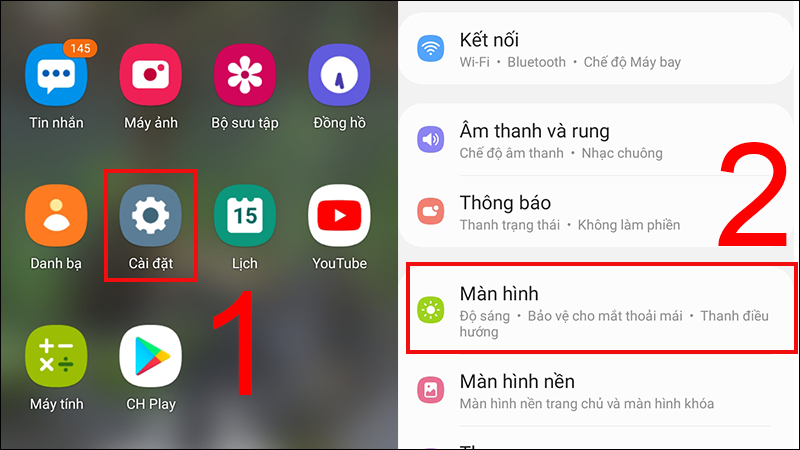
Vào cài đặt và chọn Màn hình
Bước 2: Chọn Cỡ font, kiểu font > Trong mục Cỡ Font, bạn điều chỉnh thanh công cụ từ phía cỡ chữ rất nhỏ sang rất lớn như mong muốn.
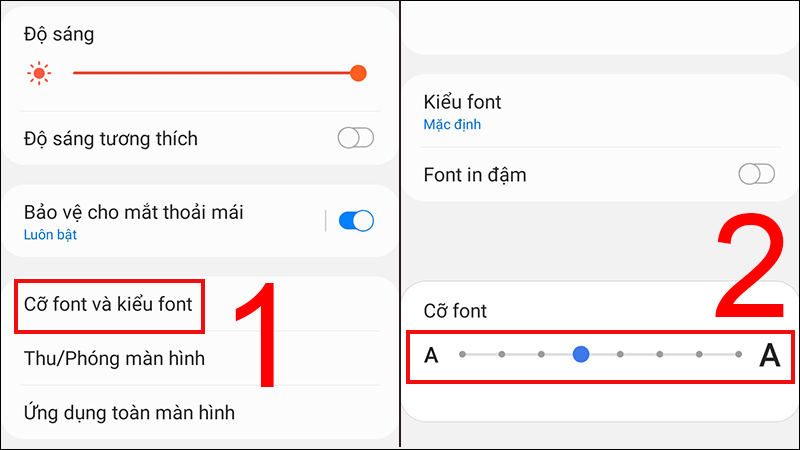
Điều chỉnh kích thước chữ
2. Cách thay đổi font chữ trên điện thoại Samsung
Hướng dẫn nhanh
Vào Cài đặt > Màn hình > Chọn Cỡ font và kiểu font > Tùy chỉnh cỡ chữ,kiểu chữ phù hợp > Chọn Kiểu font > Lựa chọn kiểu chữ có sẵn hoặc chọn Tải về font để tải về các font chữ khác.
Hướng dẫn chi tiết
Bước 1:Vào Cài đặt > Chọn Màn hình.
Chọn màn hình
Bước 2: Chọn Cỡ font và kiểu font.
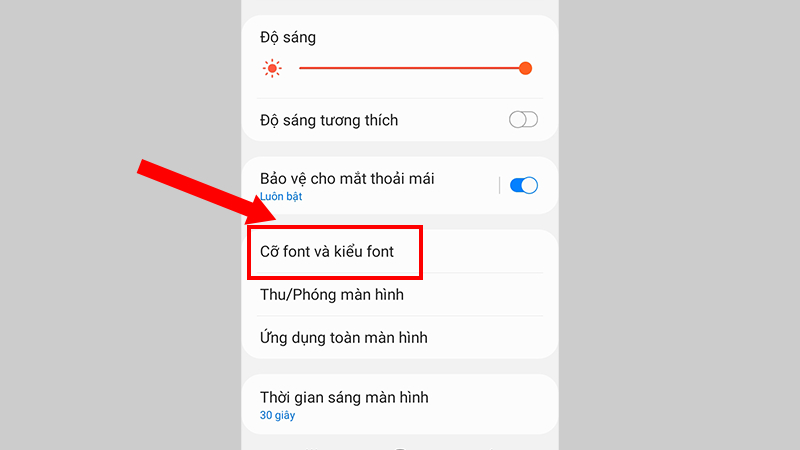
Chọn Cỡ font và kiểu font
Bước 3: Chạm Kiểu font để lựa chọn kiểu chữ có sẵn.
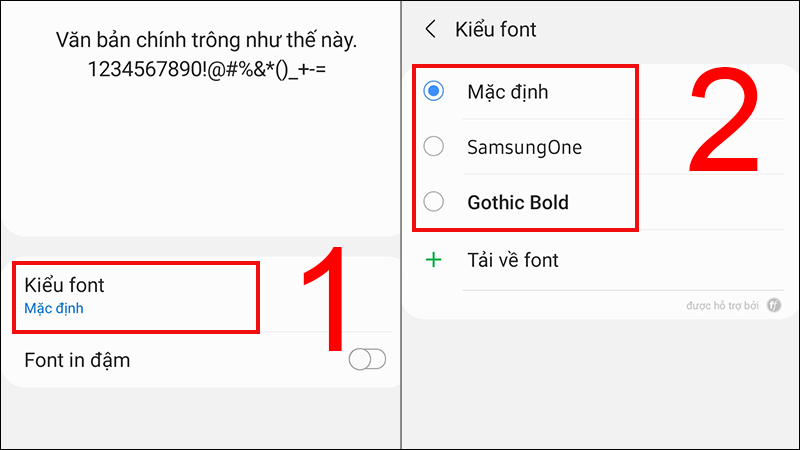
Lựa chọn kiểu chữ có sẵn
Bước 4: Ngoài ra bạn có thể bấm vào mục Tải về font để tải thêm nhiều font đẹp từ kho ứng dụng Samsung Galaxy Apps.
Tải kiểu chữ khác về máy
3. Top 10 font chữ đẹp trên điện thoại Samsung
Font chữ ZFstylish
Đây là font chữ kiểu tập lệch bút vẽ chuyên nghiệp, độ dày thay đổi và tạo ấn tượng mạnh, phong cách gọn gàng thoải mái và cảm giác ổn định, tinh tế.
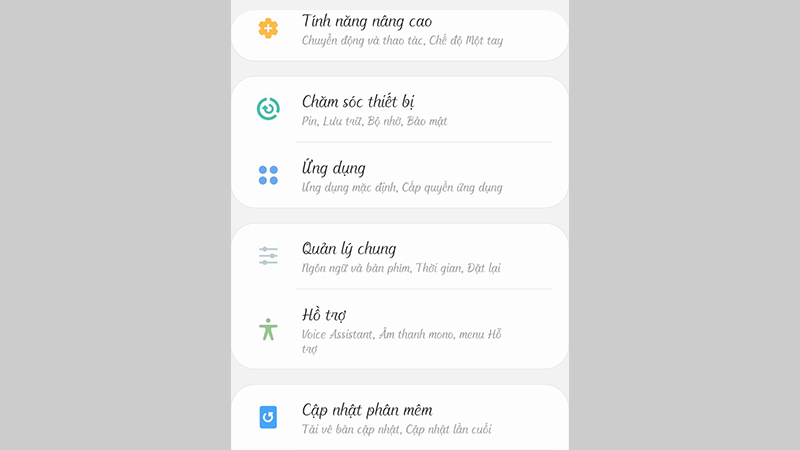
Font ZFstylish
Font chữ ZF springtime
Đây là font chữ vô cùng dễ thương và độ dày đều giúp bạn cảm nhận được năng lượng mùa xuân với những biểu cảm sống động, đáng yêu. Font chữ này chứa những ký tự cần thiết của các ngôn ngữ gốc Latin và châu Âu nên rất dễ sử dụng.
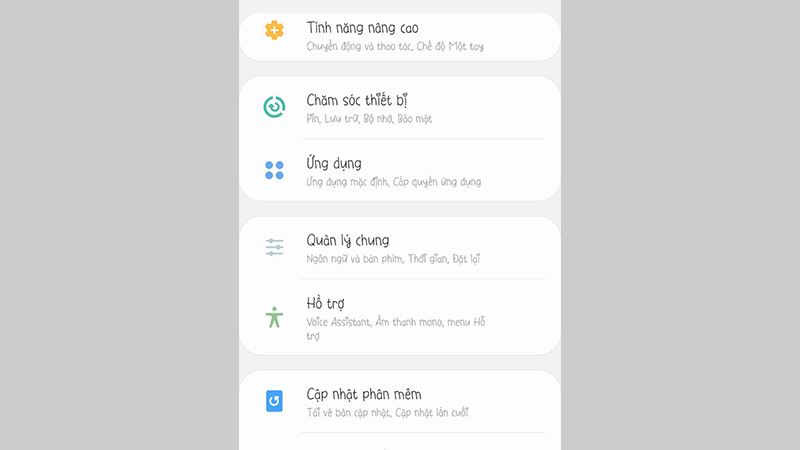
Font ZF springtime
Font chữ ZFlovewinter
Đây là loại font chữ viết tay có ít sự thay đổi về độ dày, một số chữ cái được trang trí với trái tim tạo nên vẻ đáng yêu. Với cảm hứng từ mùa đông, font chữ này sẽ đem đến những cảm xúc ấm áp khi đông về.
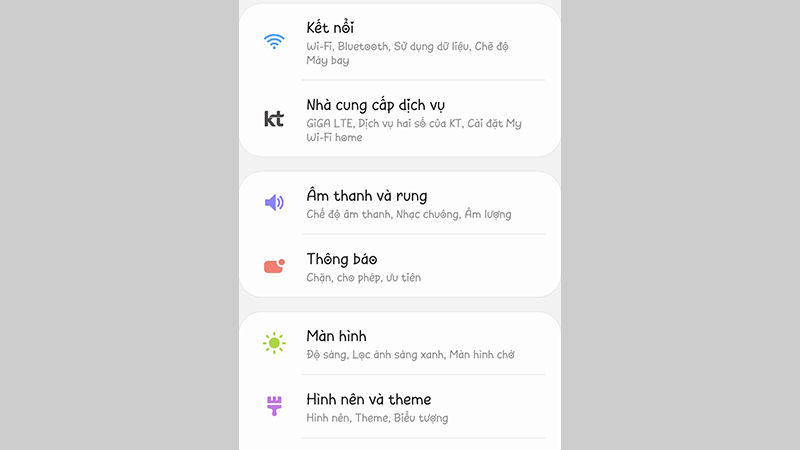
Font ZFlovewinter
Font chữ Calligraphy
Đây là font chữ có sự kết hợp hài hòa giữa những nét vẽ cong đậm và sự uyển chuyển như những nét chữ thư pháp. Sự chuyển động uyển chuyển của những con chữ sẽ đem đến cho người nhìn sự dễ chịu, hài hòa.
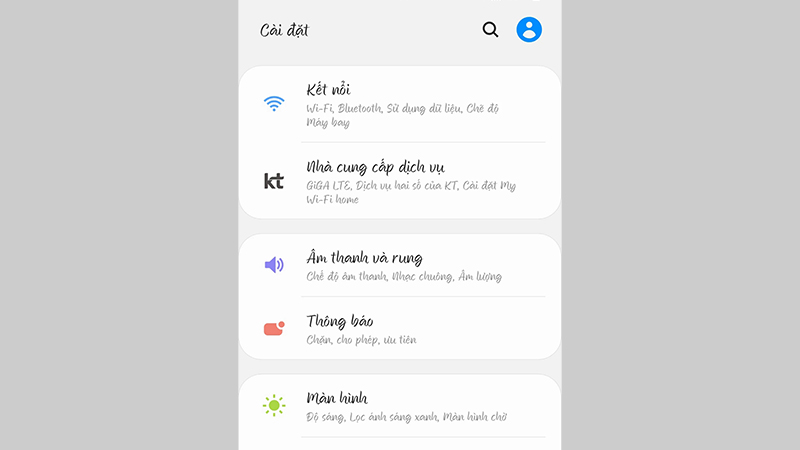
Font Calligraphy
Font chữ ZFSimplelife
ZFSymplelife là font chữ mang phong cách hiện đại với những đường thẳng và nét cong, nghiêng sang phải. Font chữ này giống như tên gọi của nó, không hề rườm rà bởi đã được cắt bỏ những nét trang trí, chúng mang phong cách tự do, đơn giản và thoải mái.
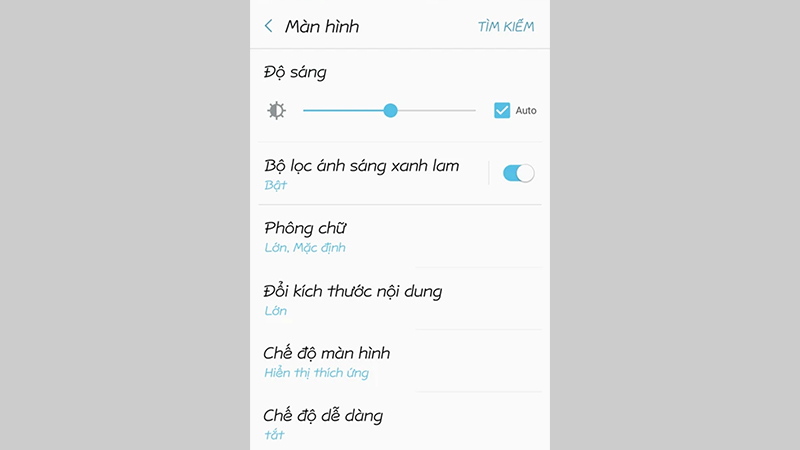
Font ZFSimplelife
Font chữ ZFholidaygift
Phong cách của font chữ này là phong cách script, nét dày đầy mạnh mẽ, đường cong mịn. Nét chữ mềm mại cùng với độ đậm vừa phải chắc chắn sẽ làm vừa lòng người sử dụng.
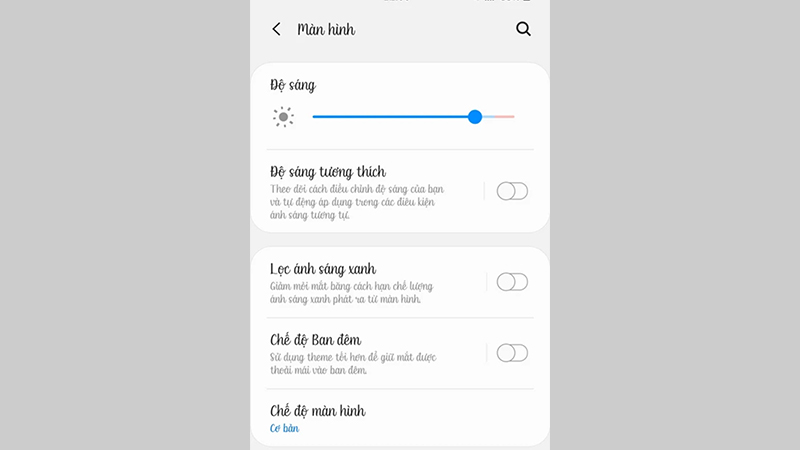
Font chữ ZFholidaygift
Font chữ ZFfirstlove
Được lấy cảm hứng từ mối tình đầu, các chữ cái nhỏ được trang trí đều nét, một số chữ còn xuất hiện hình trái tim để tạo nên không khí đáng yêu và ngọt ngào như mối tình đầu lãng mạng.Font chữ này ắt hẳn sẽ đem lại cho người dùng cảm giác vui vẻ, yêu đời.
Font chữ ZFfirstlove
Font chữ MT Hipster Script
Đây là một font chữ khá là ấn tượng bởi những con chữ này có nét phá cách ở phần đuôi chữ. Thọat nhìn cứ ngỡ những con chữ này đang nhảy múa tạo cảm giác vui nhộn cho người dùng.
Font chữ MT Hipster Script
Font chữ AhLoveRecipe Latin and Cyrillic
Font chữ này có những nét chữ từ mỏng đến khá dày mang lại cảm giác tự nhiên, mới lạ và đáng yêu.
Font chữ AhLoveRecipe Latin and Cyrillic
Font chữ DIYFancyYou
Đây là một font chữ siêu đáng yêu có chút cá tính bởi những nét chữ rất đều và rõ ràng. Nét chữ này sẽ giúp người dùng có không gian dễ chịu, thoải mái.